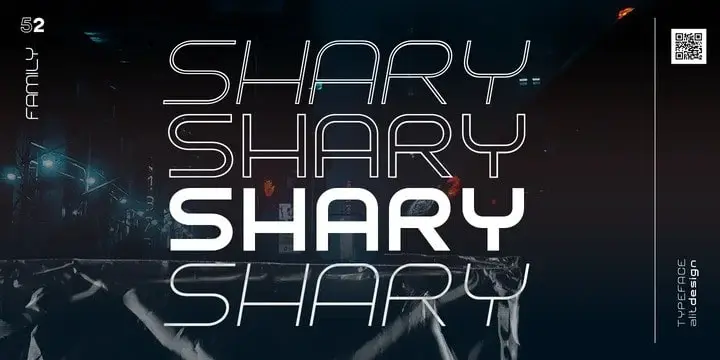
A Shary Display Font é uma tipografia moderna criada para qualquer projeto profissional que precisa de uma identidade visual atraente. Inspirada no conceito de sans serif futurista, essa fonte destaca-se com sua beleza única em cada letra. Ideal para marcas e logotipos de alta notoriedade, Shary traz uma textura audaciosa e moderna, disponível em 54 famílias que vão do fino ao grosso. Junto a ela, o conceito urbano toma um novo sentido, proporcionando um visual único e dinâmico. Esta fonte é perfeita para quem busca algo novo e impactante, seja em projetos de design gráfico ou branding. Engaje-se com a Shary Display Font e experimente uma experiência visual inovadora.